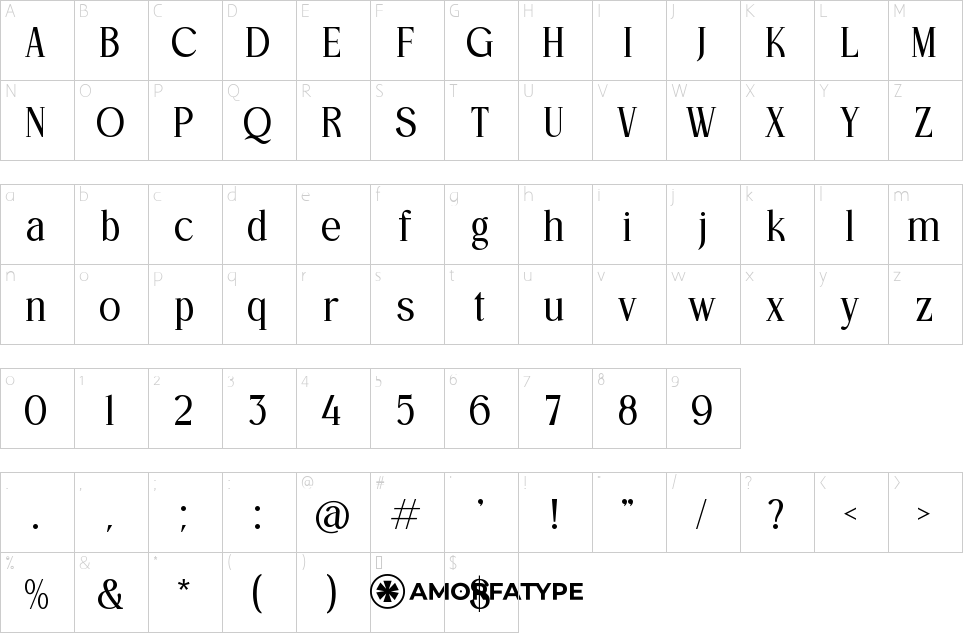
A Gangors é uma fonte de estilo moderno e elegante projetada por Amorfa Type que oferece uma variedade de opções para personalizar seu design digital. Seja você um designer profissional ou alguém procurando adicionar um toque único a suas criações, esta fonte pode fornecer exatamente o que está buscando. Com sua geometria cuidadosamente criada e estilo minimalista, Gangors oferece uma versão perfeita para aplicativos de desktop Windows e Mac, garantindo uma experiência consistente em todo o seu trabalho digital. Em um ambiente onde a customização e a personalização são valorizadas, Gangors é uma fonte que não pode ser deixada de lado, já que foi baixada 393 vezes. Instale-a agora para experimentar a diferença que ela pode fazer em suas criações digitais.